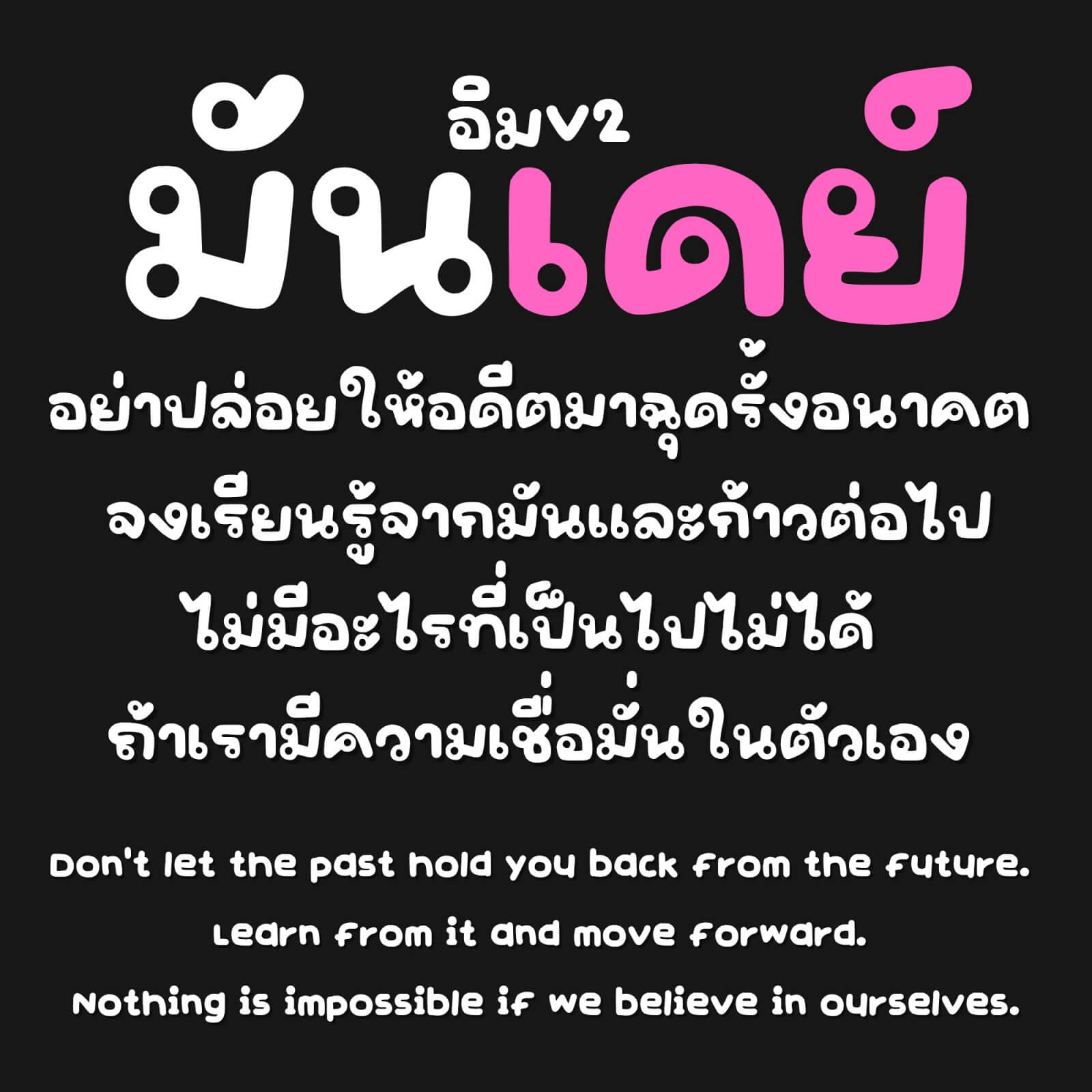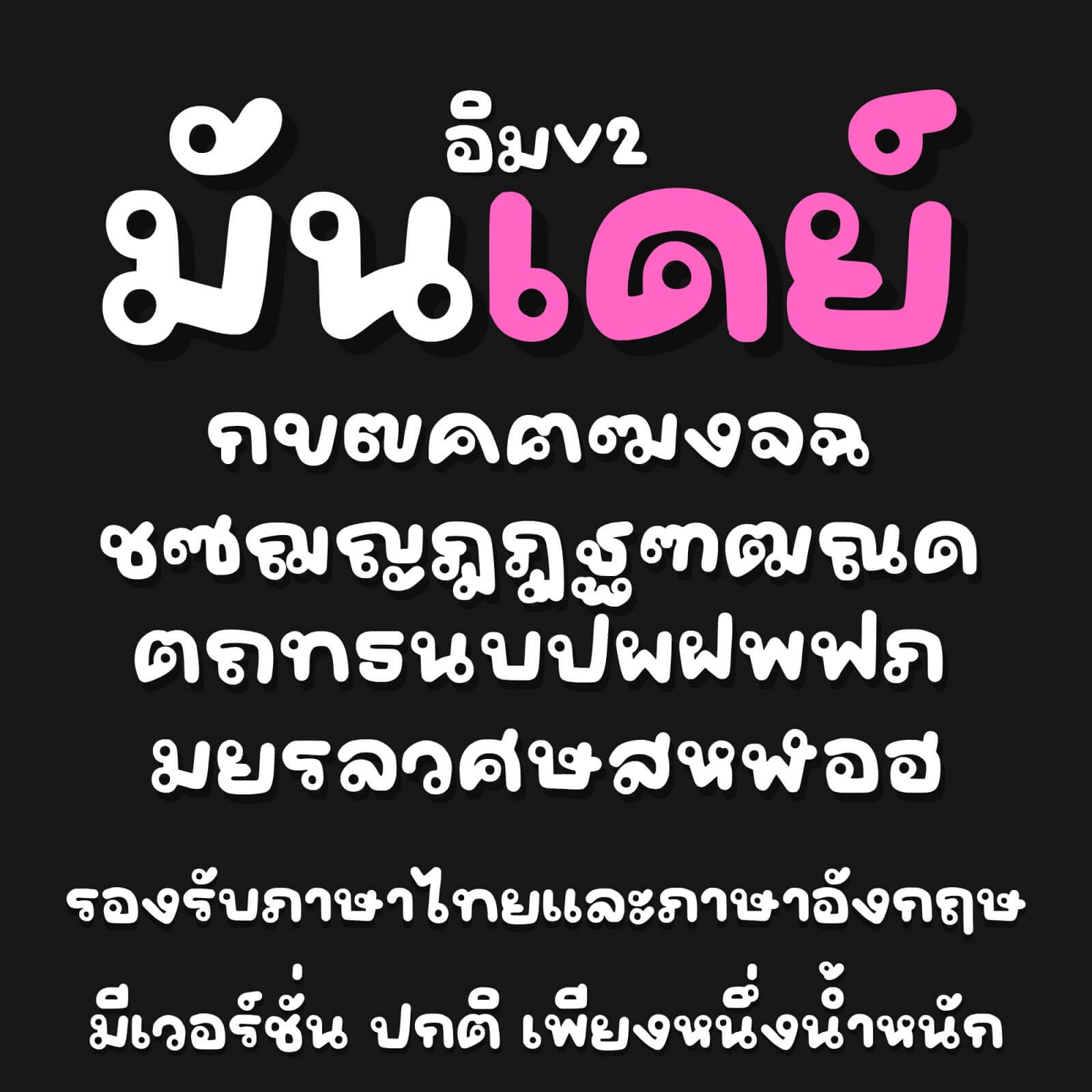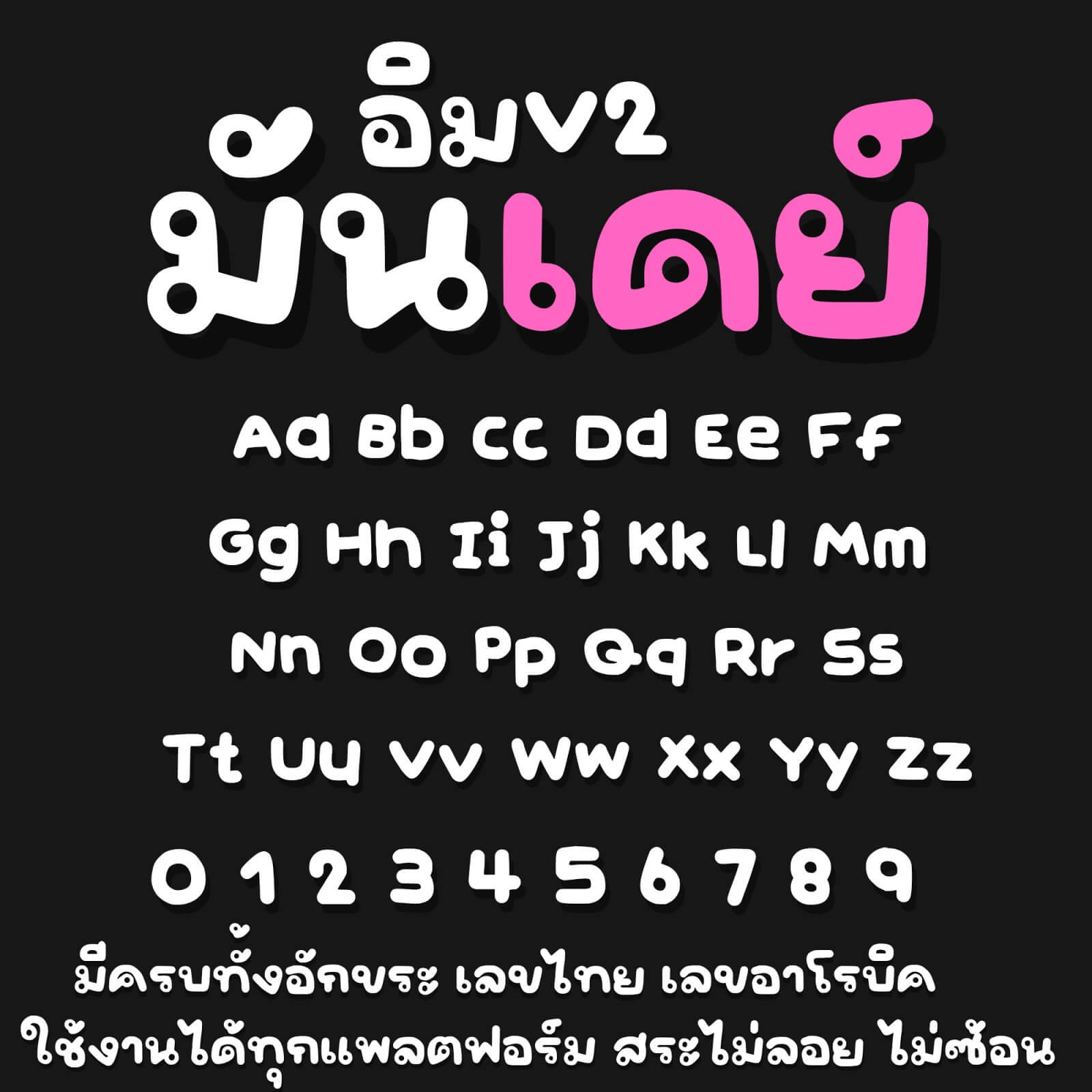
อิมมันเดย์ (IMTYC Manday)
แจกตัว Demo เพื่อทดลองใช้งานฟรี อิมมันเดย์ ฟอนต์ – ตัวอ้วนหนาเหมาะกับทุกสายงานเลยย
เหมาะกับทุกสายครีเอเตอร์ ไม่ว่าจะใช้ทำป้าย ข้อความ โพสต์ หรือคอนเทนต์น่ารักๆ